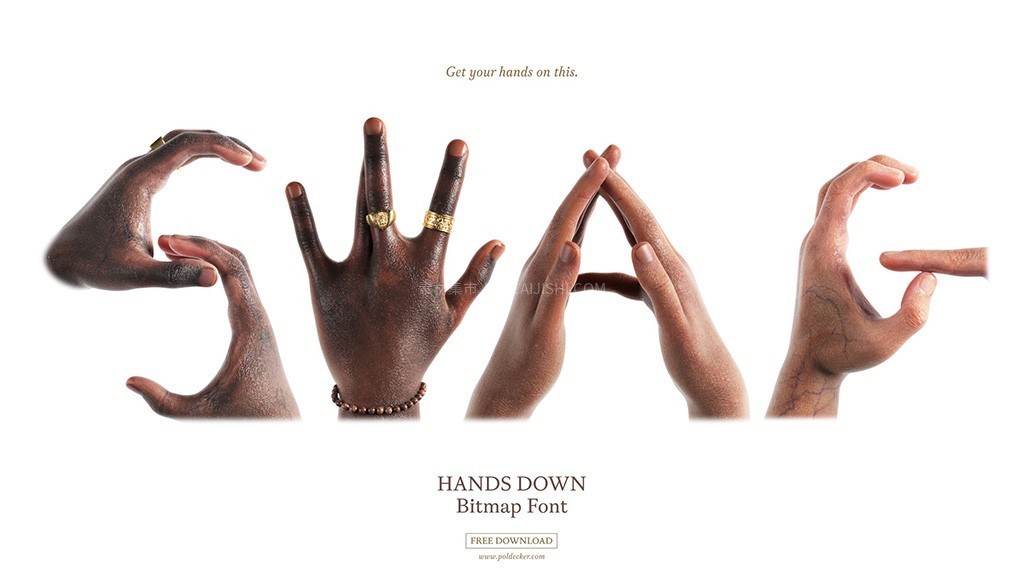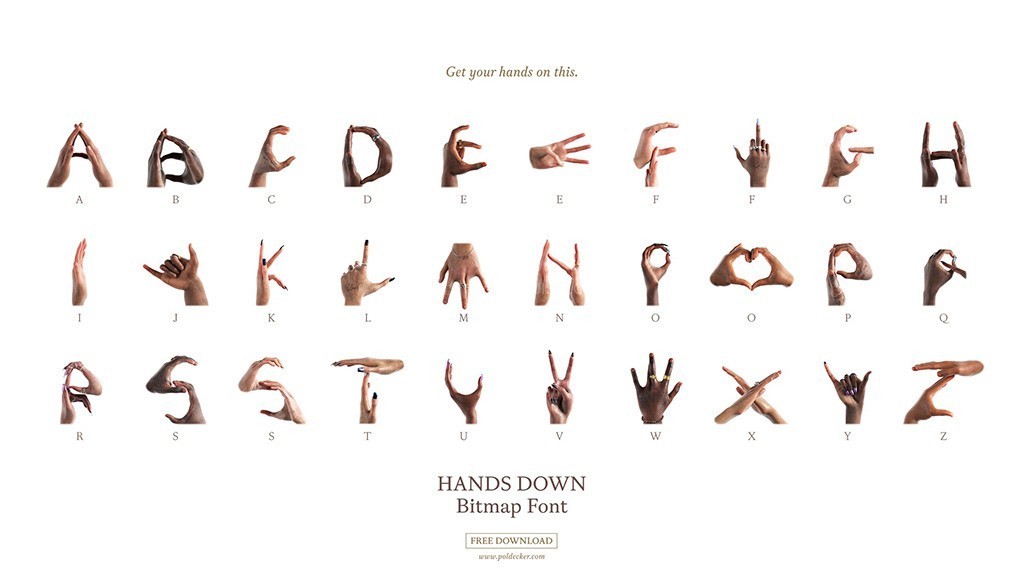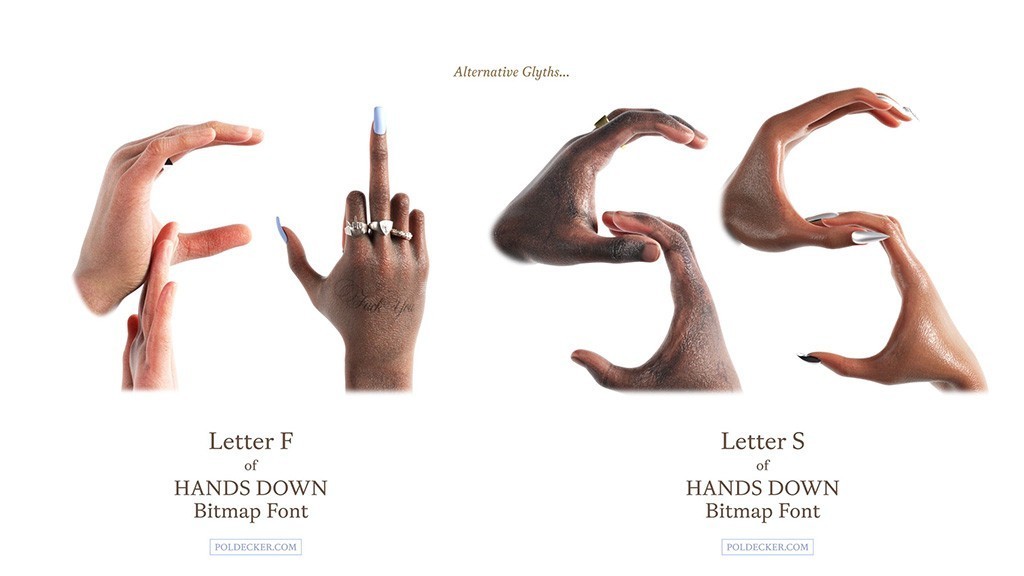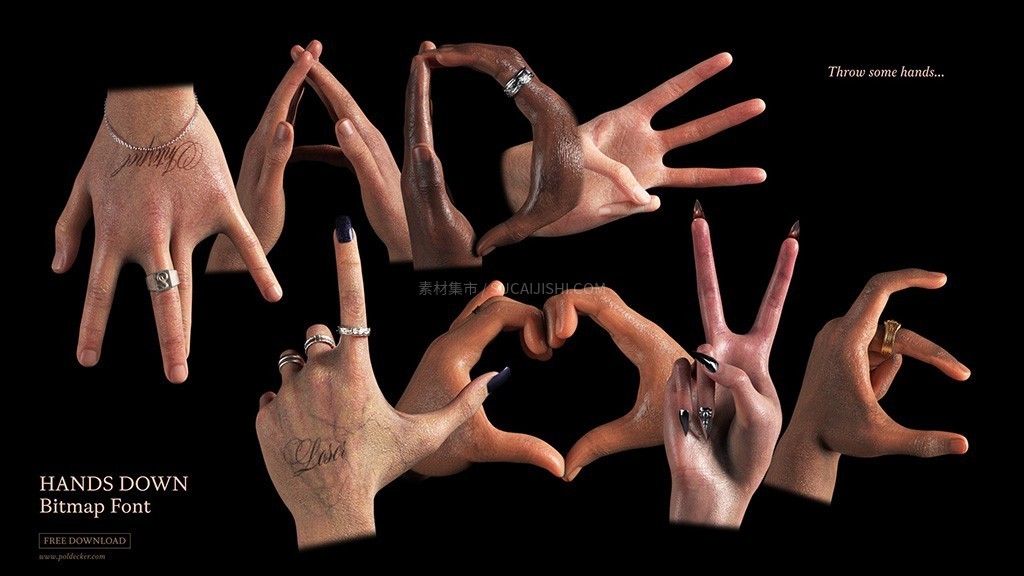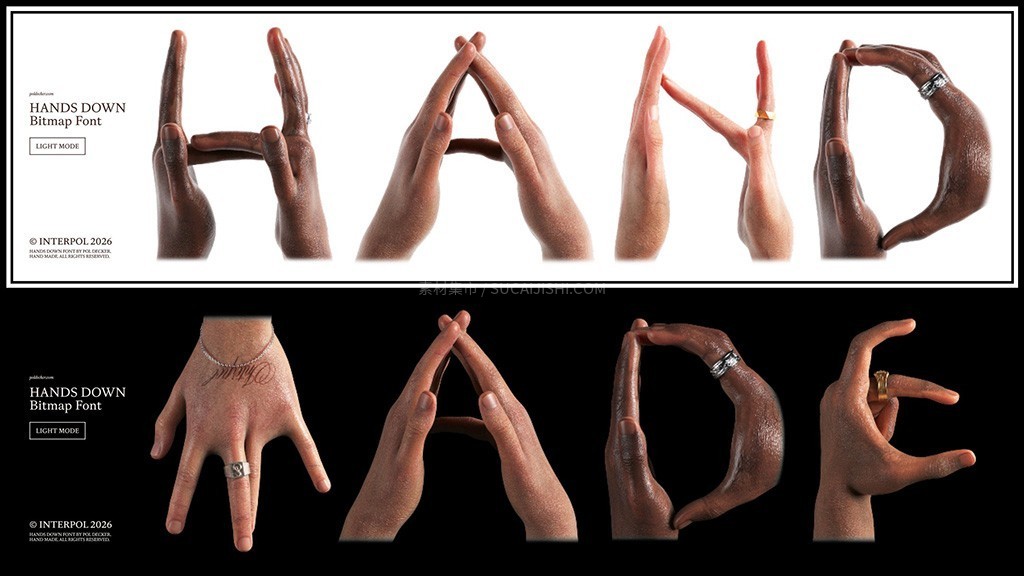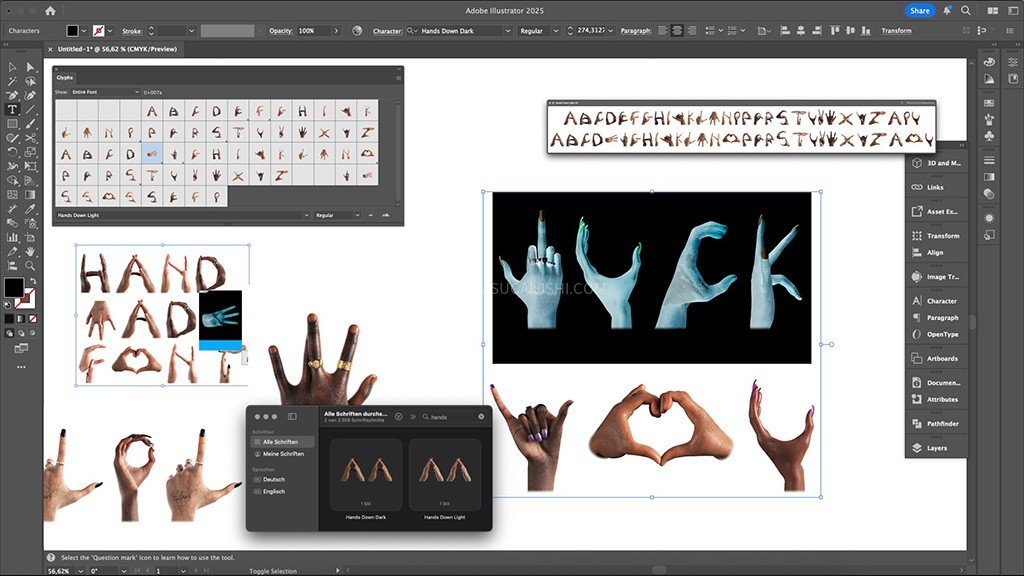
Hands Down 字母手势位图字体
这是一款完全由手部动态元素构成的精细位图字体(Bitmap Font)。它打破了传统字母的枯燥,将每一个字符都化作独特的肢体语言。无论是充满力量感的警示标识,还是极具艺术张力的海报封面,这款字体都能为你提供绝无仅有的“手感”视觉冲击力。
浅色版(Light): 完美契合白色或明亮背景。
深色版(Dark): 专为深色或黑色背景设计,轮廓分明。
特性:
高精度细节: 细腻的位图纹理,保留手部最真实的结构感。
完整字母表: 包含 A-Z 全套大写字符。
替代样式: 针对 E、F、O、S 字符提供替代字形,增加排版变化。
多环境适配: 浅色/深色双版本切换,省去后期调整色彩的烦恼。